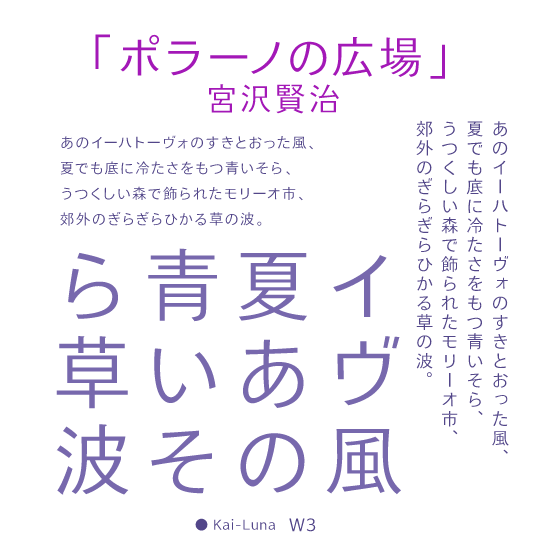
解 ルナ W3
◉電子媒体における明解な組版を探って漢字の新しいエレメントを探りました。「Luna」は横組みの視線誘導を意図しました。ちらつきを抑えた曲線と字形構成は、情報量の多い誌面において秩序を与え明瞭な組版となります。Webでも効果がみられるとおもいます。Positiveなモダン性を持っています。